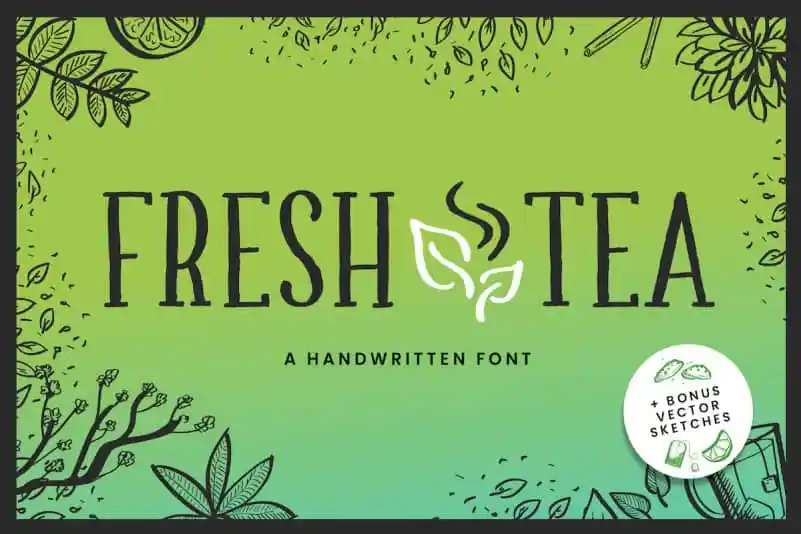
Fresh Tea - A fancy handwritten font
A “Fresh Tea” é uma moderna e elegante fonte serifada escrita a mão que vai deixar seu design de texto brilhar. Além disso, vem acompanhado de um conjunto de desenhos temáticos baseados na biodiversidade dos diferentes tipos de chá. Este projeto da shapedfonts oferece não apenas um estilo único para seus projetos gráficos e digitais, mas também uma ampla variedade de formatos de arquivo para facilitar o uso desses recursos. Os desenhos temáticos incluídos no pacote estão inspirados em diferentes tipos de chá, desde chás verdes e amarelos até chás de ervas temperadas, e cada um oferece a oportunidade de explorar a beleza artística do design a mão. Se você é fã de desenhar ou criativamente manipular textos, pode experimentar a demo gratuita “Fresh Tea” com o intuito de encontrar exatamente como essa fonte se encaixa em seu próximo projeto. Como um benefício adicional para os usuários que compram o produto, você também poderá usar a demo sem limites para projetos pessoais e não comerciais gratuitamente. Essa é uma ótima maneira de testar as capacidades da “Fresh Tea” antes de incorporá-la em seu trabalho final.